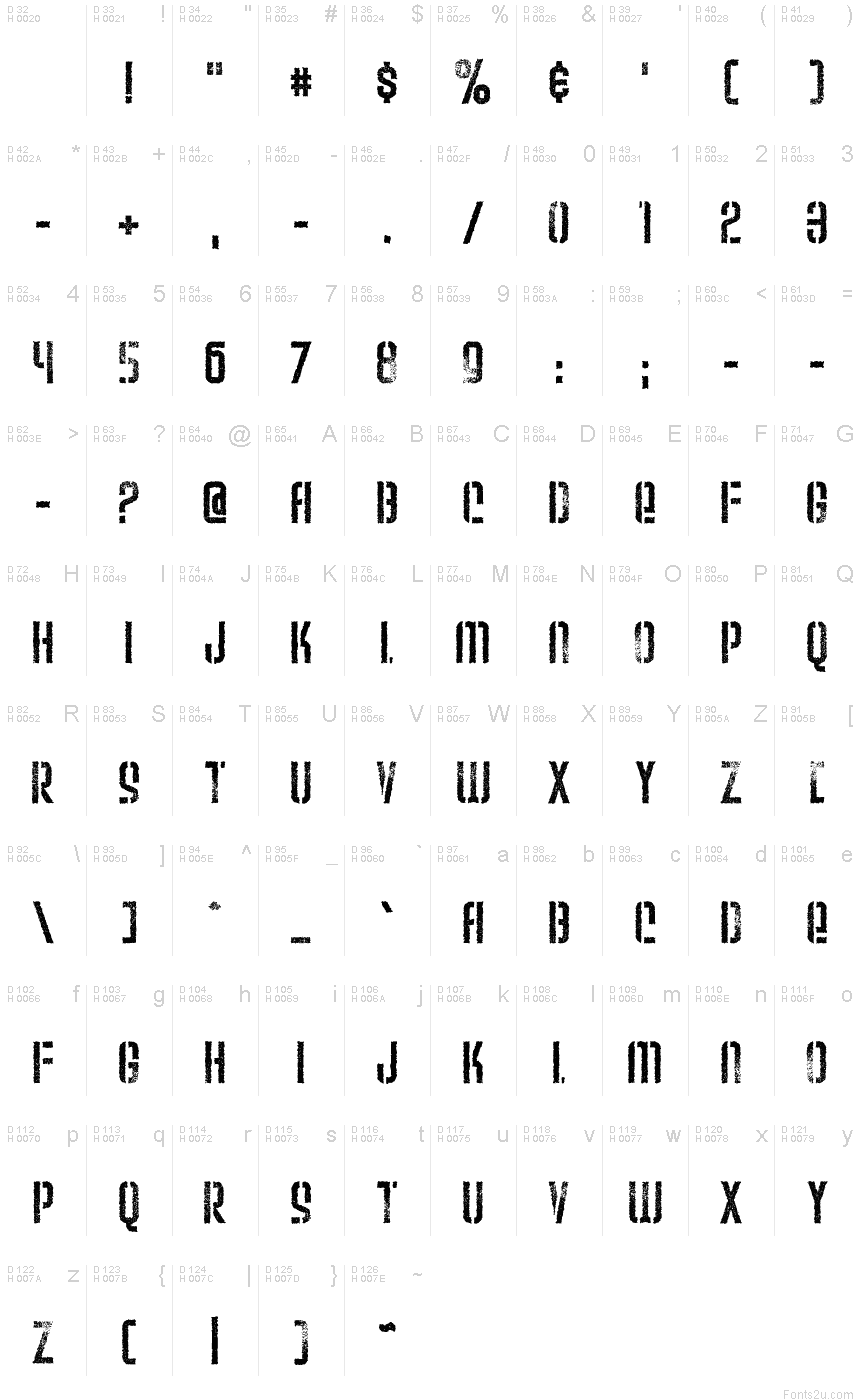
Weltron Urban
Weltron Urban od Font"a"licious Fonts to darmowy, erozyjny krój typu display, utrzymany w surowym klimacie ulicznych plakatów z końca lat 90. Litery wyglądają, jakby zostały wyryte w łuszczącej się farbie, a nierówne pionowe kreski i poszarpane krawędzie nadają całemu zestawowi szorstki, miejski rytm – daleki od sterylnego, industrialnego wykończenia.
To naturalny wybór do klubowych ulotek, grafik deskorolkowych, okładek płyt, plansz tytułowych czy krótkich nagłówków na plakatach, gdzie faktura gra główną rolę. Jako darmowy font z 2001 roku, Weltron Urban świetnie sprawdza się w krótkich, mocnych akcentach – liniach na okładkach, logotypach czy napisach z efektem pieczątki – ponieważ jego postarzane wielkie litery błyskawicznie wprowadzają klimat zużycia, szumu i dynamiki.